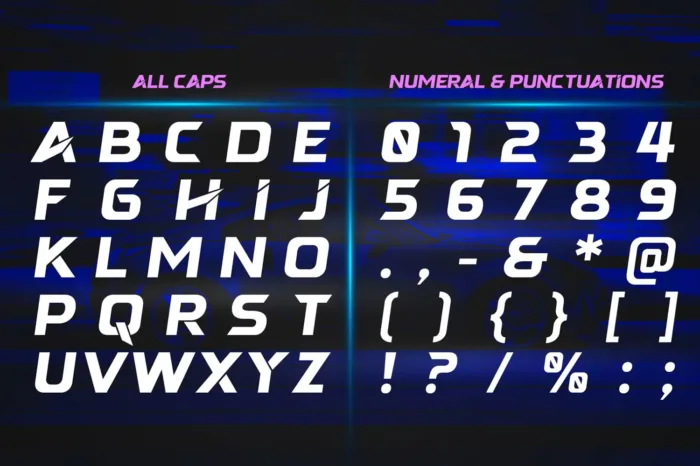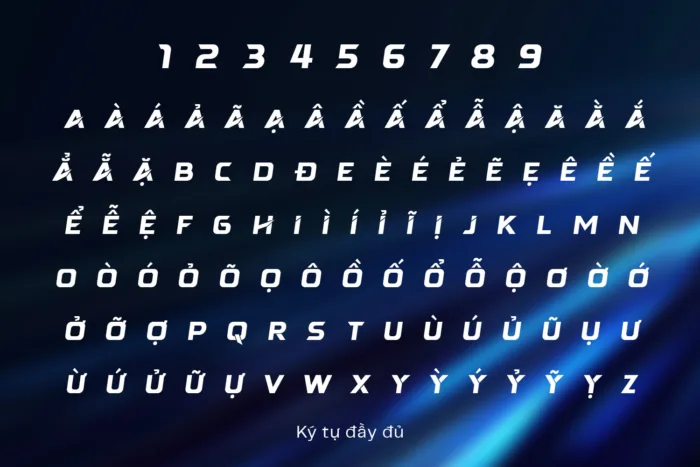
DVN Sakana Việt hóa – Font chữ đậm chất công nghệ, thể thao
DVN Sakana là font chữ viết hoa toàn bộ mang đậm tinh thần tốc độ và công nghệ hiện đại. Thiết kế nghiêng, sắc nét và dứt khoát giúp tạo hiệu ứng thị giác mạnh, phù hợp cho các dự án liên quan đến game, xe đua, thể thao điện tử hay các sản phẩm truyền thông mang tính năng động. Font hỗ trợ đầy đủ tiếng Việt, bao gồm cả số và dấu câu, giúp bạn dễ dàng áp dụng trong nhiều hoàn cảnh sáng tạo. DVN Sakana đặc biệt hiệu quả khi dùng trong tiêu đề, poster, banner kỹ thuật số hoặc các dự án branding mang hơi hướng tương lai và táo bạo. Một lựa chọn lý tưởng để truyền tải năng lượng, tốc độ và cá tính trong từng thiết kế.